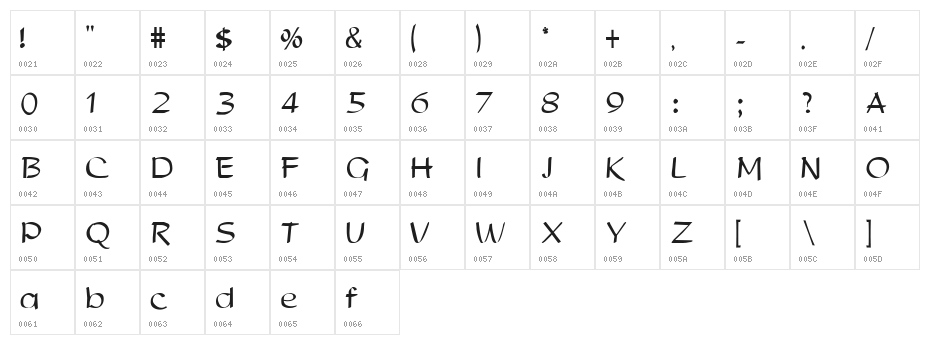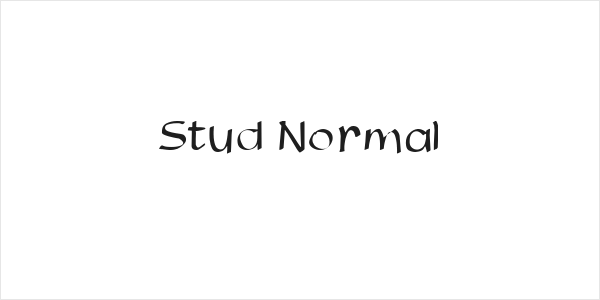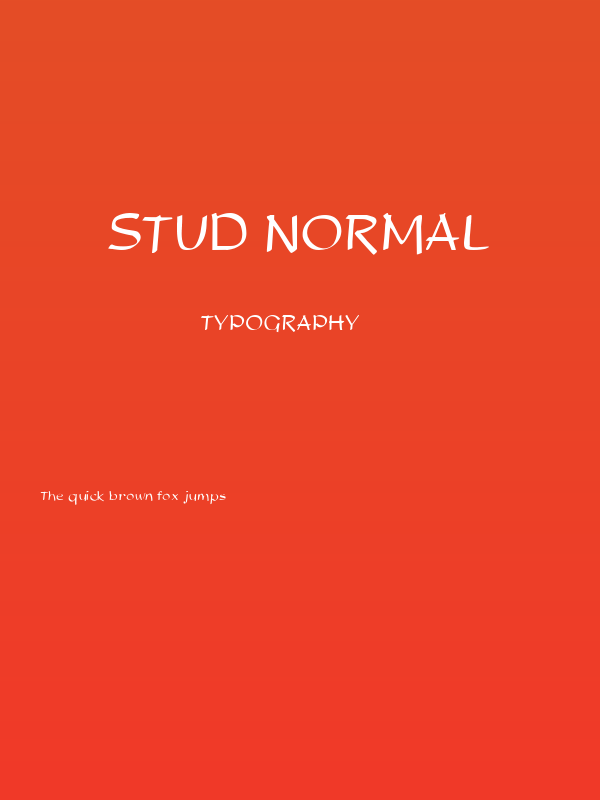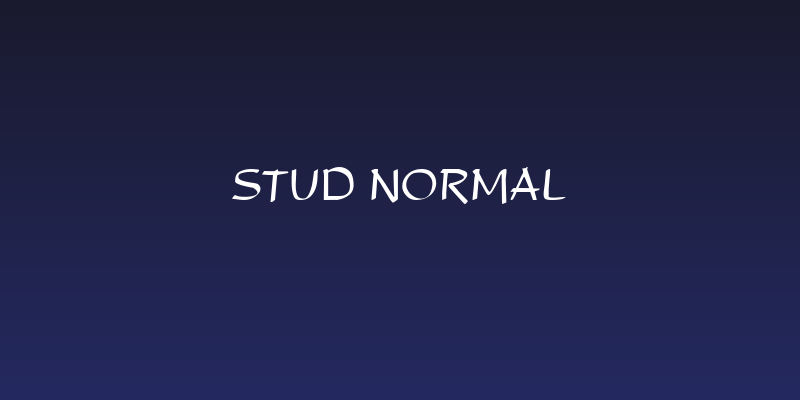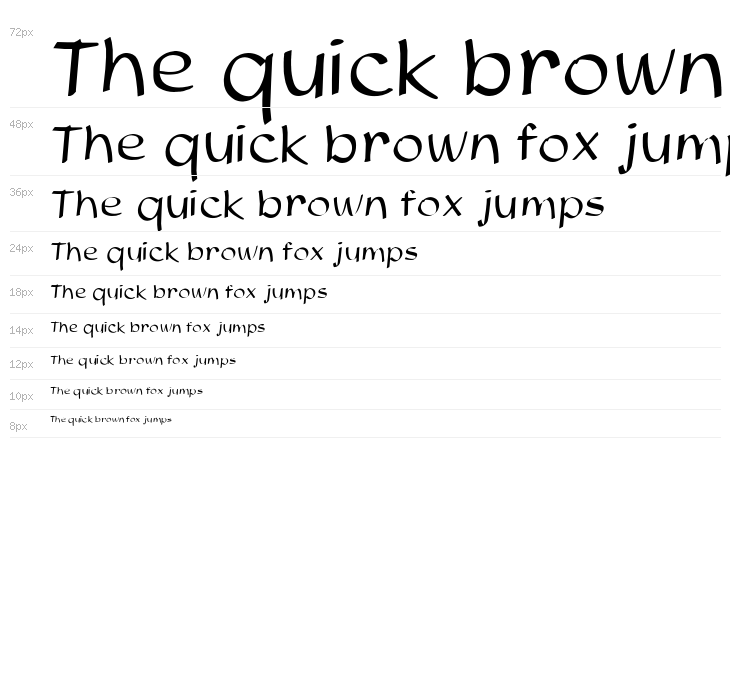
Stud Normal Font
| Style général | Casual |
| Cas d'utilisation | Logos, Headlines, Informal Text |
| Projets proposés | Ideal for greeting cards, children's books, playful branding, and informal invitations. |